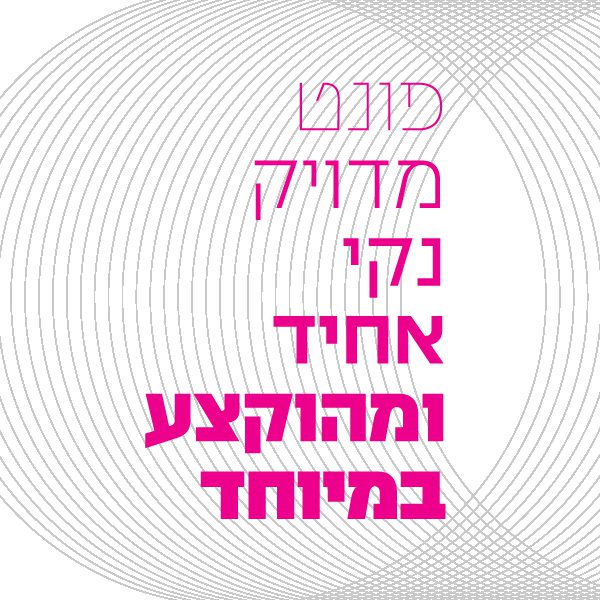
מונופולי
מונופולי / Monopoly
• שם הגופן:מונופולי
• מעצב הגופן:נדב עזרא
• סגנון:סאן סריף
• מאפיינים: דקיק קל רגיל בינוני כבד שחור
• תכונות: אלגנטי מגזיני מודרני מרובע משולש פשוט קוסמטי קלאסי קשיח
סיפור הגופן:
גופן לא צפוי, שמשחק על מערכת יחסים בין צורות גיאומטריות. הגופן מגיע בהשראת כיתוב שהופיע על גבי מפת מונופול ישנה. הייחוד שלו מתבטא במראה שבלוני חד ומדויק להפליא. זהו טיפוס רב-לשוני ורב משקלים, בעל מבנה עוצמתי לטקסט ולדיספליי.